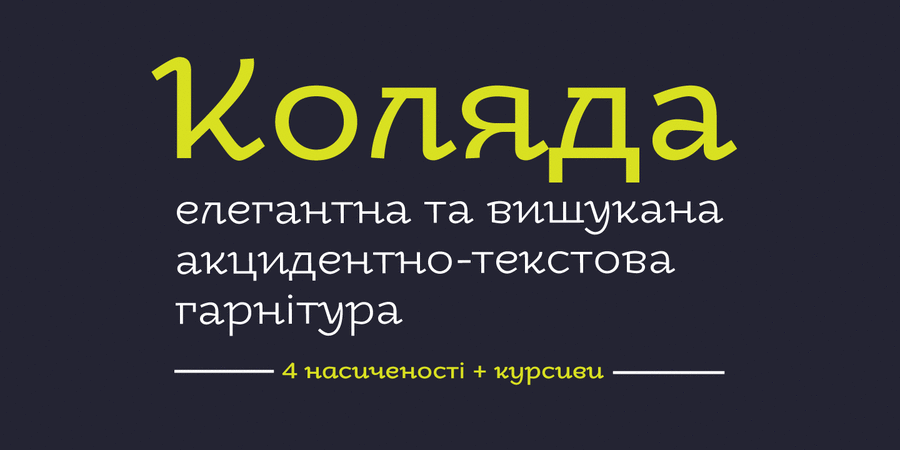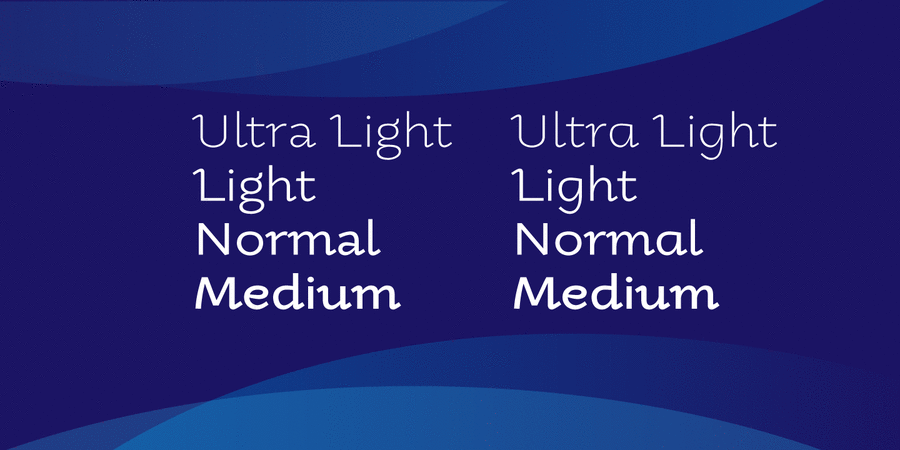
Коляда – сучасний антиква-гротеск із доброзичливим характером. Цей шрифт підходить для використання у торгівлі, рекламі, журналах, логотипах, книжках тощо. Він поставляється у 4 варіантах жирності від Надтонкого до Середнього з натуральним прямим курсивом для кожного. Шрифт був розроблений Кирилом Ткачовим у 2013 році.
Асоціації з сімейством шрифтів KolyadaОсобистість і характер гарнітури:
свіжий, лихий, розв'язний, легкий, тонкий, природний, натуральний, дотепний, живий, органічний, оригінальний, самобутній, чесний, характерний, етнічний, традиційний, козацький, вольний, колоритний, артистичний, художній, динамічний, вільний, цікавий, акуратний, гуманітарний, доброзичливий, рукотворний, ритмічний, відкритий, довірчий, виразний, культурний, ремісничий, прикольний, весняний, племінний, мирний, добрий, активний, здоровий, бадьорий, веселий, задерикуватий, радісний, літній, святковий, пластичний, гнучкий, щедрий, теплий, приємний, різдвяний, домашній, сімейний, яскравий, сміливий, помітний, рясний, насичений
фольклор, музика, дієта, природа, весна, вишиванка, графіка, ілюстрація, ранок, світанок, пейзаж, танець, торгівля, історія, література, театр, реконструкція, ремесло, відпочинок, туризм, табір, гумор, дитяча книжка, гра, культура, літо, банкнота, різдво, сік, дім, козак, їжа, закуска, спеції, свято, здоров'я, монета, мед Гарнітура має ознаки стилів: